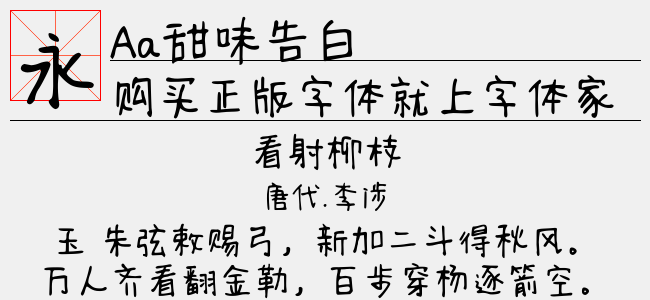
Aa甜味告白 字体大小5.04 M,包含了6763个汉字以及附加其他英文字体和阿拉伯数字,属于Aa字体。Aa甜味告白(TTF)可以免费下载,商业用途请自行购买版权,它的特征就是手写,个性,手书风格,内文,采用安装嵌入的安装方式,支持符号拉丁文日文中文等语言
字体作者:Aa字体
字体名称:Aa甜味告白